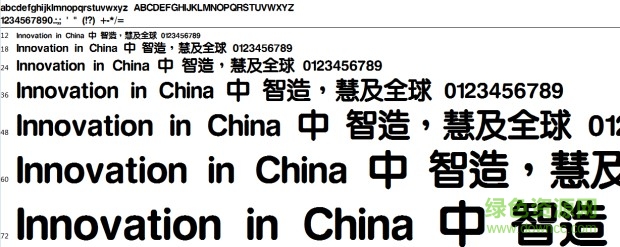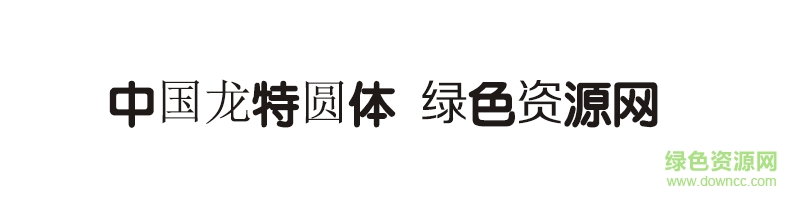
中國龍?zhí)貓A體
中國龍?zhí)貓A體是一款非常圓潤的字體,這款字體軟件也是人們非常廣泛使用的一款字體,感興趣的朋友就來綠色資源網(wǎng)下載體驗(yàn)吧!
中國龍?zhí)貓A體特點(diǎn)
中國龍?zhí)貓A體是一款粗圓體的字體,字體整體非常圓潤,形象美觀柔和,顯示清晰易懂,適用于多種設(shè)計(jì)環(huán)境中。